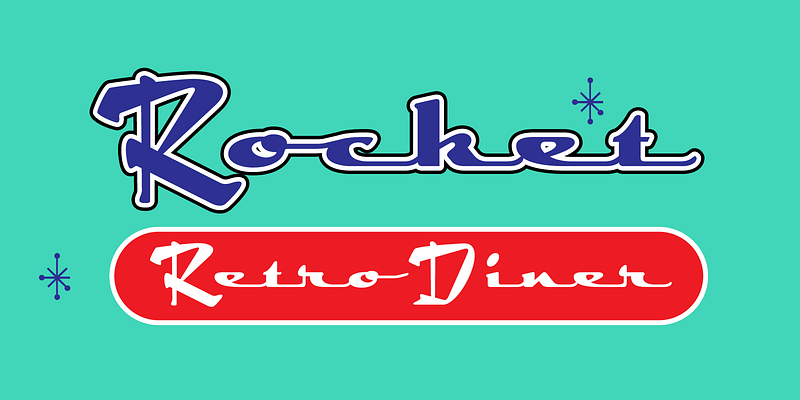
Enfin, une écriture connectée ultra-atomique pour le nouveau millénaire, ramenée des années 1950 par Leslie Cabarga. Pour créer cette police cool, ce dernier s’inspire des logos de la deuxième vague des restaurants diners américains, avec leurs bandes d’acier inoxydable et de verre que l’on voyait partout dans tout le pays à la fin de la guerre. Les frites grasses et les voitures énergivores sont peut-être le revers de la médaille des fabuleuses année 50. Il met à l’honneur le bon côté de la grande exubérance de ces scripts écrits à la main ; FB 1995.
Zavier Cabarga a dessiné des images et des caractères toute sa vie. « Le dessin exige une perception inhérente de l’anatomie et de la proportion. Il en va de même pour la typographie, car je crois que nos anciennes lettres sont basées sur les proportions humaines », explique Zavier. « C’est d’abord les bandes dessinées qui m’ont inspiré, puis j’ai commencé à copier des logos et des caractères de titrage que je trouvais dans des magazines. À 15 ans, j’ai décapé des négatifs pour former une police de photocomposition brute mais utilisable. »
Travaillant sous le nom Handy Lettering Co. pendant de nombreuses années, Zavier a créé des caractères à la main pour des clients du secteur de la publicité tout en travaillant à temps plein comme illustrateur. « Dessiner des illustrations a toujours semblé difficile, alors qu’écrire, c’est facile et amusant », explique Zavier. « Je travaille depuis 25 ans sur Macintosh, ce qui m’a permis de créer des polices d’ordinateur, ce qui, à bien des égards, est la chose la plus satisfaisante que je fasse. Taper une lettre ou un caractère manuscrit avec une police que j’ai créée me donne l’impression d’être Dieu ».